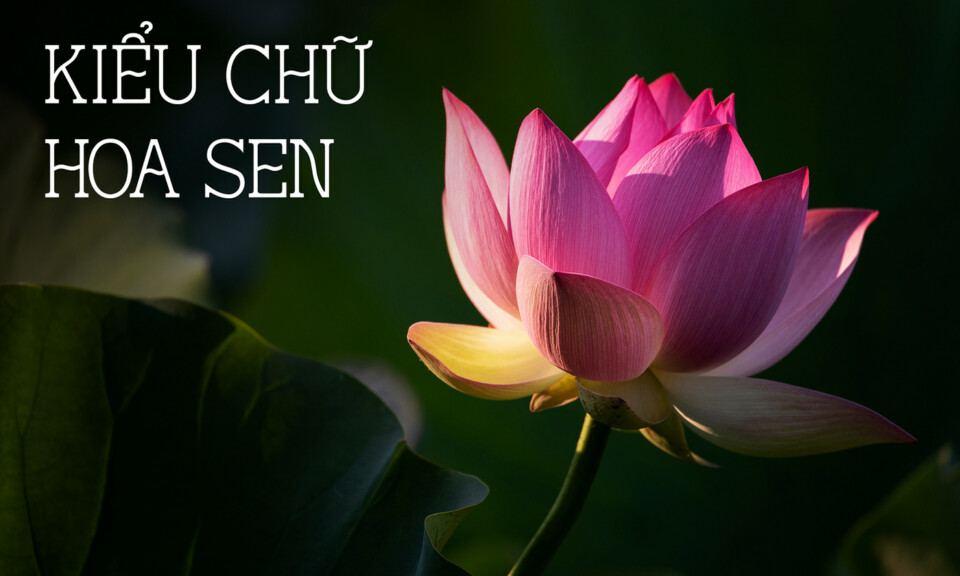
Font Tiếng Việt Hoa Sen Typeface – Kiểu chữ Hoa Sen: Nét đẹp di sản trong thiết kế hiện đại
Font Tiếng Việt Hoa Sen Typeface – Kiểu chữ Hoa Sen là một tác phẩm nghệ thuật chữ viết độc đáo, lấy cảm hứng từ hình tượng hoa sen thanh cao – quốc hoa của Việt Nam. Trong lĩnh vực thiết kế đồ họa, việc lựa chọn một Font Miễn Phí nhưng vẫn đảm bảo tính thẩm mỹ và bản sắc dân tộc là điều vô cùng quan trọng. Bộ font này không chỉ đơn thuần là các ký tự, mà còn mang trong mình hơi thở của văn hóa truyền thống, sự mềm mại nhưng đầy kiêu hãnh của những cánh sen Việt.
Ý nghĩa thiết kế của Font Tiếng Việt Hoa Sen Typeface – Kiểu chữ Hoa Sen
Đường nét mang tính biểu tượng
Đặc điểm nổi bật của bộ chữ này chính là sự kết hợp hài hòa giữa các nét bo tròn mềm mại và những điểm nhấn góc cạnh tinh tế. Mỗi chữ cái được chăm chút kỹ lưỡng để mô phỏng sự vươn lên mạnh mẽ của búp sen từ bùn lầy. Điều này giúp các ấn phẩm thiết kế trở nên có hồn và sâu sắc hơn.
Tính ứng dụng linh hoạt trong giáo dục
Nhờ phong cách trang trọng và dễ đọc, bộ chữ rất phù hợp để sử dụng trong các tài liệu giảng dạy, bài trình chiếu thuyết trình hay các ấn phẩm truyền thông tại học đường. Kiểu chữ giúp học sinh tiếp cận với cái đẹp truyền thống một cách tự nhiên thông qua các trang sách và bài giảng hàng ngày.
Cách sử dụng Font Tiếng Việt Hoa Sen Typeface hiệu quả
Để phát huy tối đa vẻ đẹp của bộ font, người dùng nên kết hợp với các tông màu trung tính hoặc màu sắc mang hơi hướng hoài cổ như đỏ đô, vàng đồng. Bộ font này cực kỳ ấn tượng khi dùng làm tiêu đề cho các dự án văn hóa, bìa sách hoặc poster sự kiện nghệ thuật. Với định dạng font tiếng Việt chuẩn, bạn sẽ không gặp bất kỳ lỗi hiển thị dấu câu nào khi soạn thảo văn bản.